Как изменить шрифт в Discord и форматировать сообщения
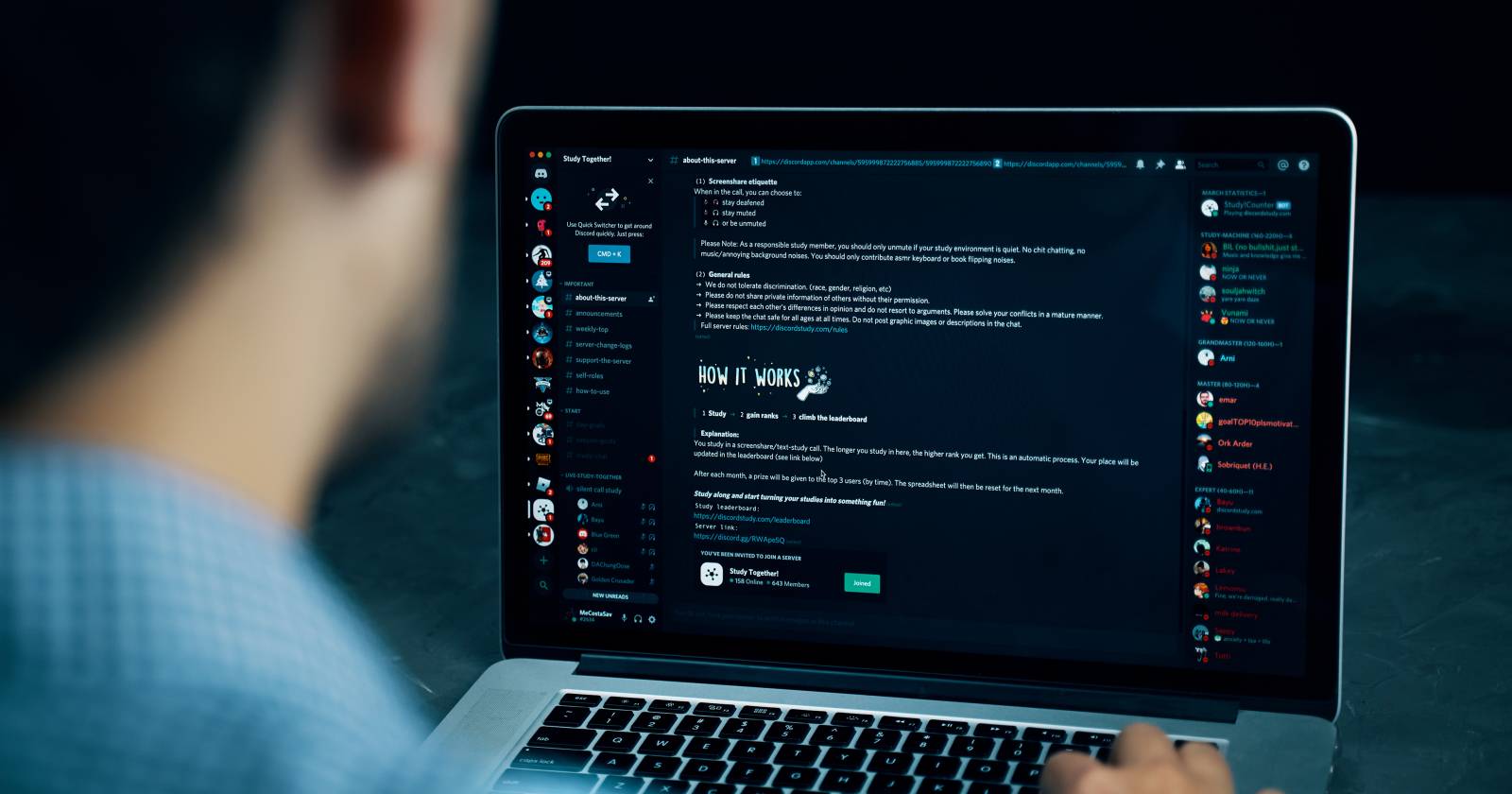
Введение
Если вы часто сидите в Discord — будь то общение с друзьями, координация игр или работа в сообществе — естественно захотеть настроить интерфейс под себя, включая шрифты. К сожалению, смена системного шрифта клиента не предусмотрена официально. Тем не менее есть несколько рабочих подходов, которые дают визуальные изменения либо меняют вид ваших сообщений.
Важно: в статье перечислены как официальные настройки, так и обходные пути. Обходные решения (моды, сторонние клиенты) могут противоречить правилам Discord — используйте их осознанно.
Краткая схема решений
- Официальные настройки интерфейса: масштаб, размер текста и расстояние между группами сообщений.
- Для оформления отдельных сообщений: генераторы «красивого текста» (Unicode), Markdown, блоки кода с подсветкой для цветов.
- Моды/стили (BetterDiscord, Powercord): полная кастомизация CSS, но риск нарушения правил.
Как поменять шрифт клиента (официально доступные варианты)
Discord использует фирменный шрифт gg sans по умолчанию, и встроенной опции «выбрать шрифт» нет. Зато в настройках доступны инструменты, которые влияют на читаемость и визуальное восприятие текста.
На компьютере (Windows, macOS, Linux)
- Доступные параметры:
- Chat font scaling — масштаб шрифта сообщений (меняет размер шрифта в сообщениях).
- Space between message groups — расстояние между группами сообщений от одного пользователя.
- Zoom level — общий масштаб интерфейса (увеличивает всё окно клиента).
Изменения отображаются в превью (кроме Zoom, который применяется сразу). Все настройки сохраняются автоматически.
На мобильных устройствах (iOS и Android)
- Доступно меньше опций: Zoom level и Classic chat text size (классический размер текста). Нажмите Save, чтобы сохранить.
Использование сторонних инструментов для смены шрифта в клиенте
Есть модификации и расширения, которые позволяют применять собственные CSS-стили к Discord (например, BetterDiscord, Powercord и аналоги). Они дают возможность: менять шрифт интерфейса, настраивать отступы, цвета, вид юзербаров и т. д.
Important: Такие инструменты официально нарушают условия использования Discord. Разработчики модов часто пишут в FAQ, что гарантий от реакции Discord нет; используете на свой страх и риск. Помимо возможных санкций со стороны платформы, сторонние моды могут содержать уязвимости или эксплуатировать ваши локальные данные.
Как использовать «разные шрифты» в тексте сообщения
Discord не даёт выбрать системный шрифт для каждого сообщения, но есть приёмы, которые визуально меняют текст.
Способ 1 — генераторы шрифтов (Unicode)
Онлайн-генераторы (Fancy Text, Font Space, Font Generator Guru и др.) преобразуют ваш текст в последовательности похожих Unicode-символов. Вы копируете получившийся «стиль» и вставляете в сообщение.
Плюсы:
- Лёгко и быстро.
- Работает везде (настольный клиент, мобильное приложение, веб).
Минусы:
- Технически это не обычный шрифт, а набор похожих символов Unicode. Поисковые и автоматические системы (например, боты) могут работать иначе с такими строками.
- Длинный текст может выглядеть странно или нарушать читабельность.
Пример использования:
- Откройте генератор, введите строку.
- Выберите стиль, нажмите Copy.
- Вставьте в Discord и отправьте.
Способ 2 — Markdown для форматирования
Discord поддерживает Markdown — простой синтаксис для выделения текста. Это не меняет шрифт, но подчёркивает структуру и делает текст заметнее.
Краткий набор:
| Формат | Markdown | Горячая клавиша | Результат |
|---|---|---|---|
| Курсив | текст или текст | Ctrl + I | Курсив |
| Жирный | текст | Ctrl + B | Жирный |
| Подчёркнутый | текст | Ctrl + U | Подчёркнутый |
| Зачёркнутый | Ctrl + Shift + S | Зачёркнутый |
Также можно комбинировать (например, жирный и подчёркнутый).
Совет: выделяйте фрагменты для внимания; не злоупотребляйте, чтобы не ухудшать восприятие.
Способ 3 — блоки кода и подсветка для имитации цвета
Код-блоки оформляются тройными обратными апострофами (), после которых можно указать язык. Discord применяет подсветку синтаксиса, и некоторые комбинации языков/тегов дают однородный цветный вывод. Также использование code-fence меняет шрифт на моноширинный (Consolas в настольном клиенте). Пример минимального блока кода (моноширинный шрифт): Ваш текст здесь
Чтобы использовать подсветку для цвета, укажите язык сразу после трёх апострофов. Ниже приведены практические примеры, которые часто применяют для получения нужного вида:
Красный текст (и красный фон для изменений diff):
- Ваш текст здесь[Ваш текст здесь]
Тёмно-синий текст:Ваш текст здесьСиний текст:“Ваш текст здесь”Светло-голубой текст:Зелёный текст (и зелёный фон для изменений diff):